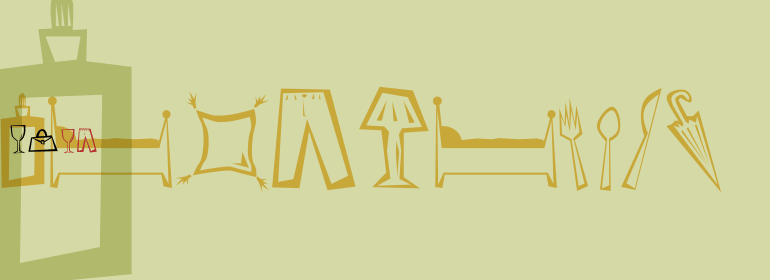
Radicals™
Radicals™,这款字体结构工整、笔画清晰,兼顾美观与易读性,适用于标题、正文、海报、包装、LOGO 等多种场景。字形优雅稳定,风格百搭耐看,适配日常排版与创意设计,让文字呈现更舒适、更具质感。Radicals™一笔一画,皆是细节,以均衡的比例、流畅的线条打造舒适视觉体验,字形端正大气,风格简约现代。无论是商业设计、品牌宣传还是日常排版,都能轻松驾驭,让文字更有格调与力量。Radicals™字体下载。